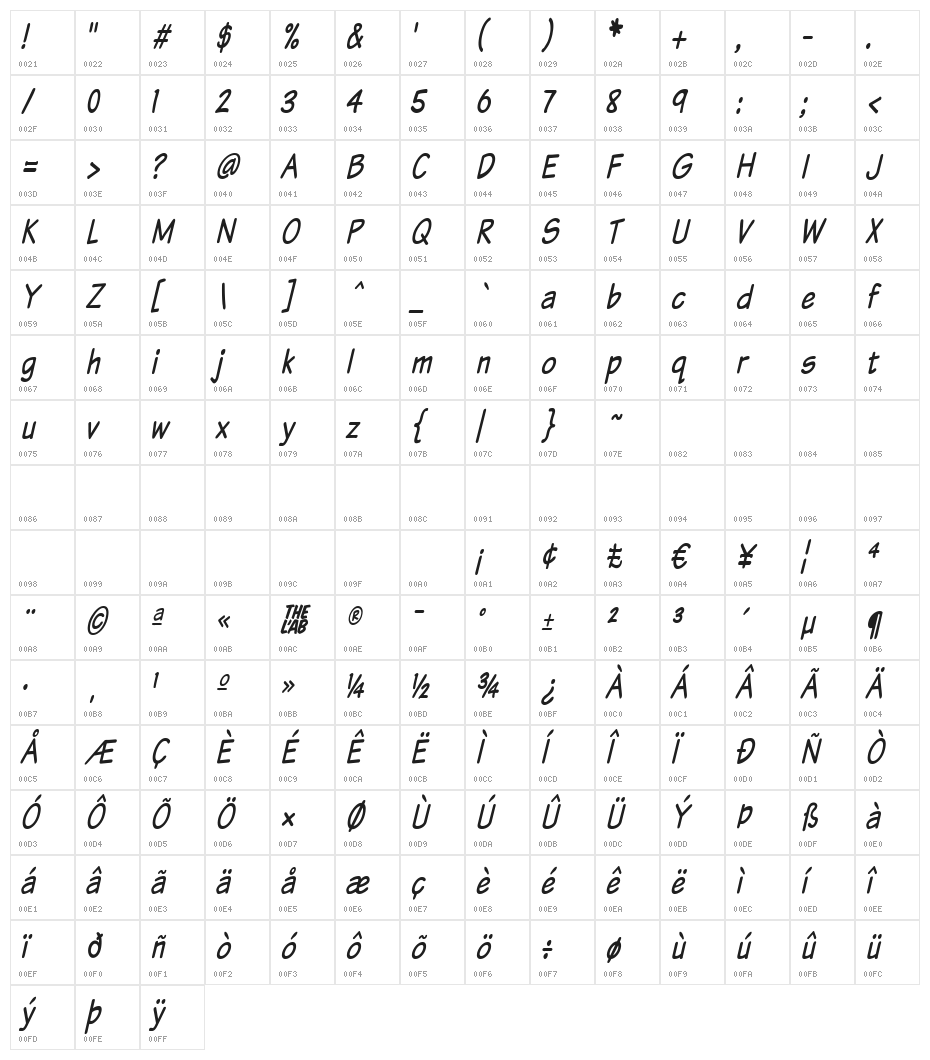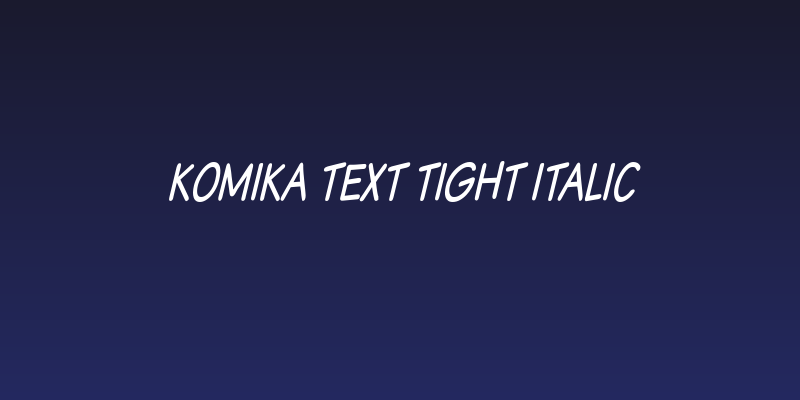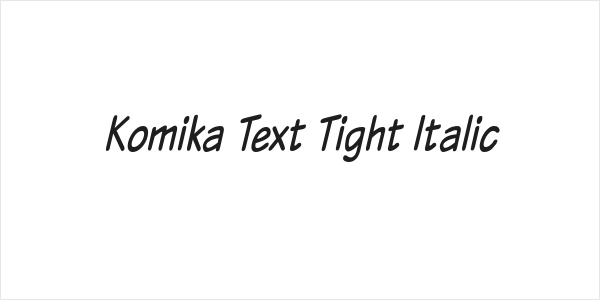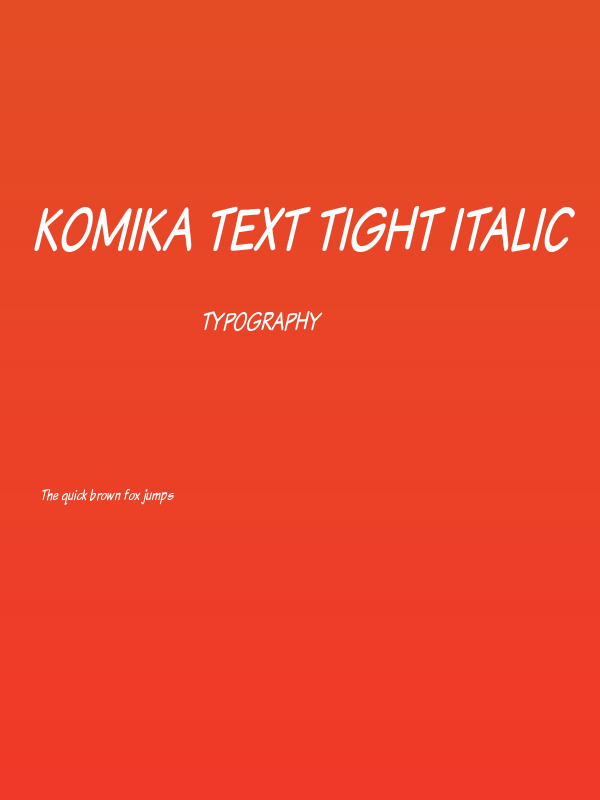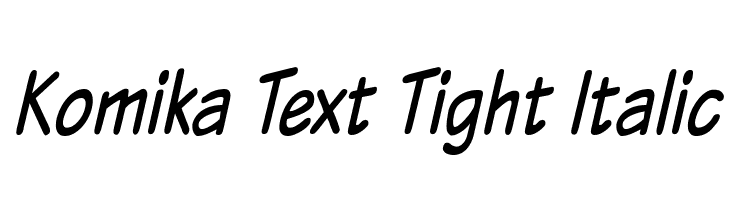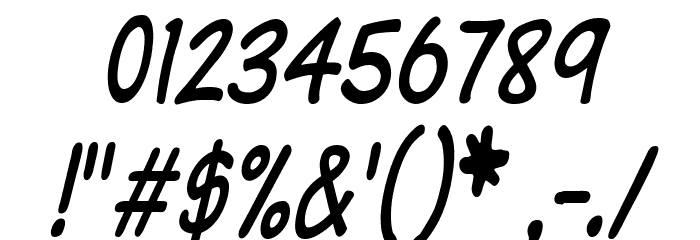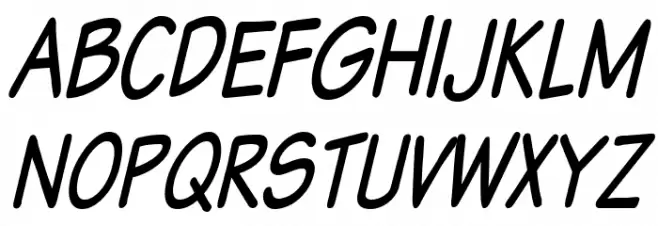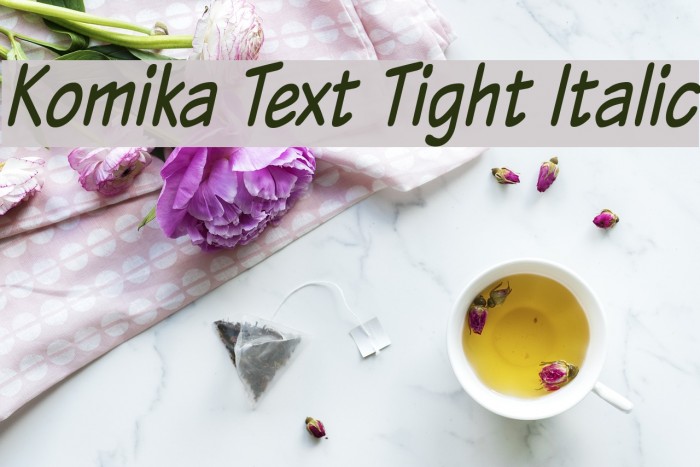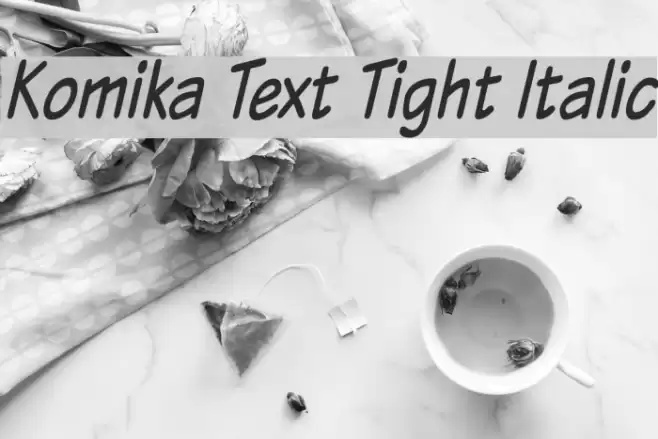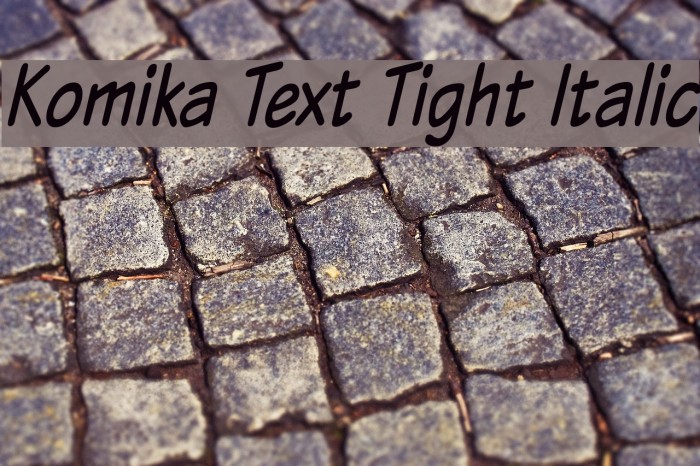
Komika Text Tight Italic Font
| Categorie | Comic |
| Stile generale | Playful, Informal |
| Caso d'uso | Headlines, Logos, Informal Text |
| Progetti proposti | Ideal for comic books, children's books, playful branding, greeting cards, and informal invitations. |